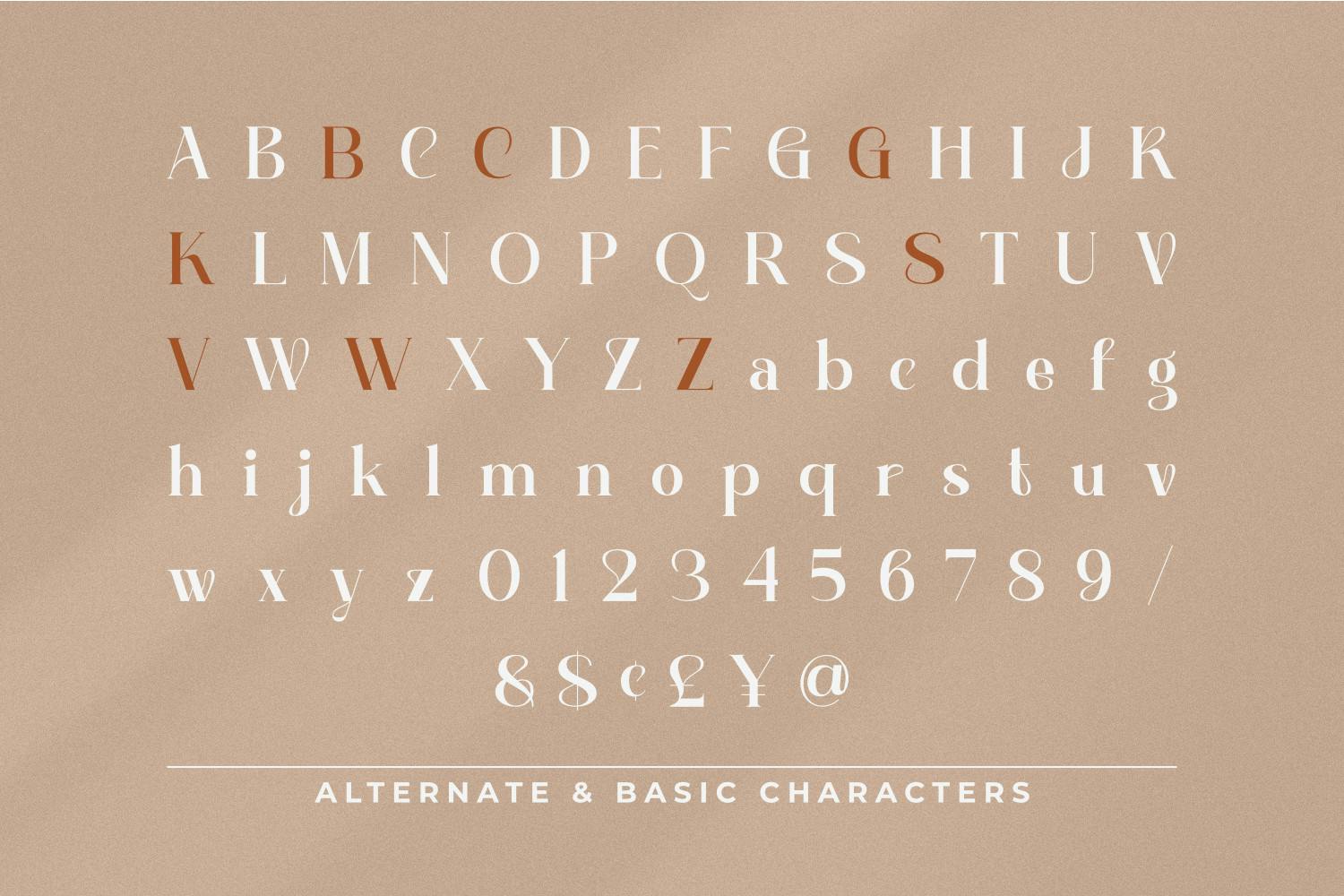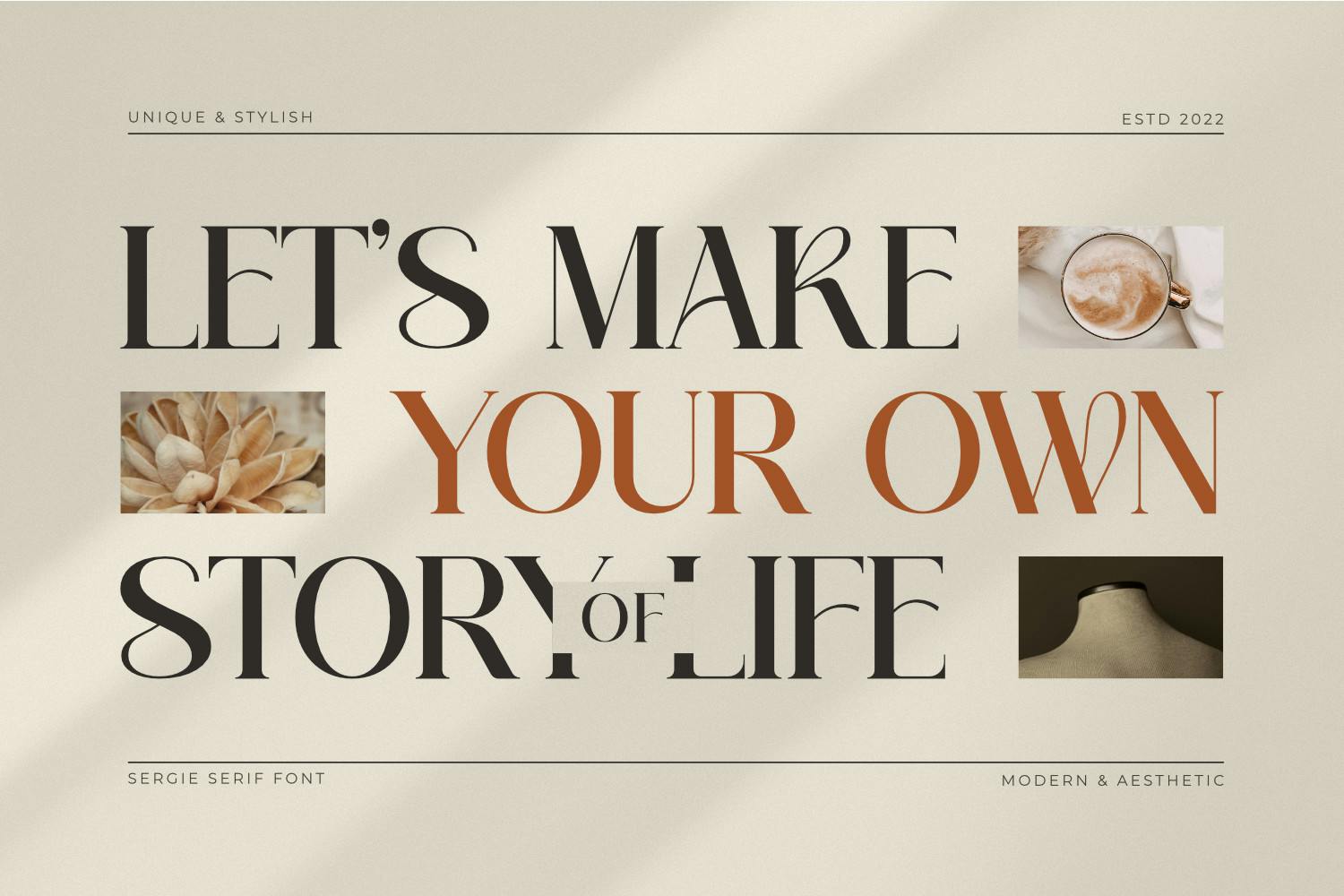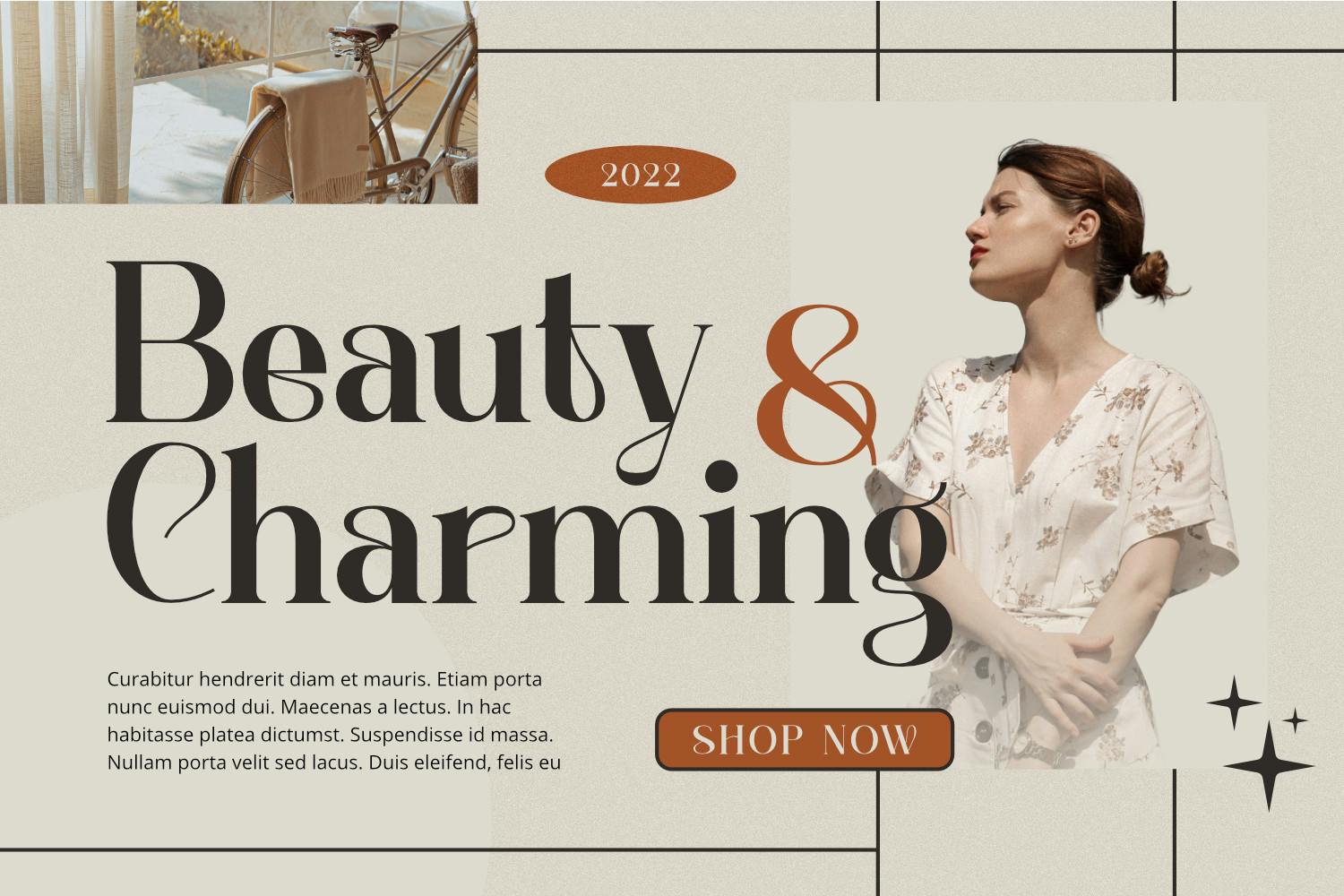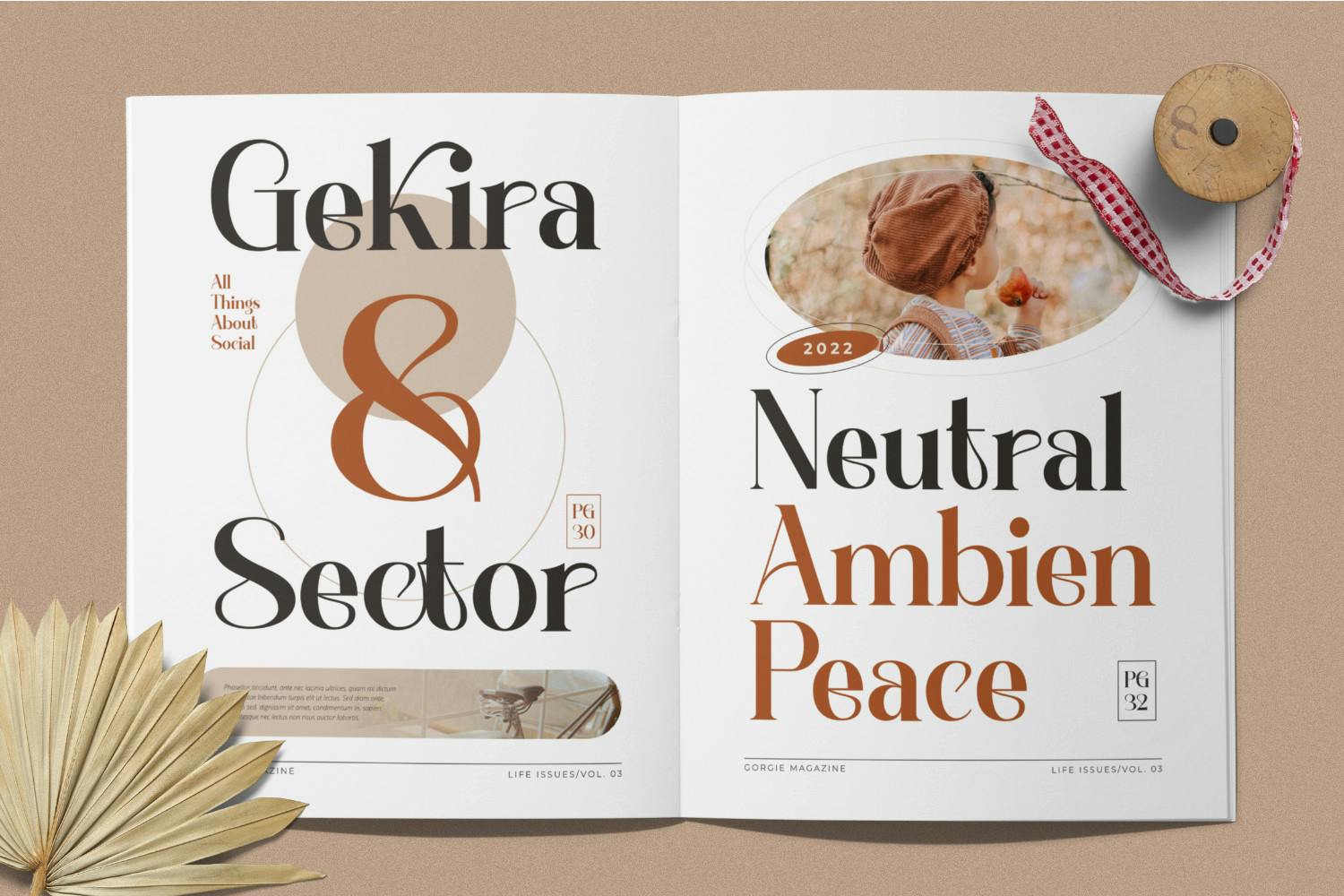
فونت Sergie برای بسیاری از پروژههای شما مانند لوگو و برندینگ، عکاسی، دعوتنامهها، واترمارکها، تبلیغات، طراحی محصولات، لوازمالتحریر، طراحیهای عروسی، برچسبها، بستهبندی محصولات، رویدادهای خاص و موارد بسیار دیگر ایدهآل است.